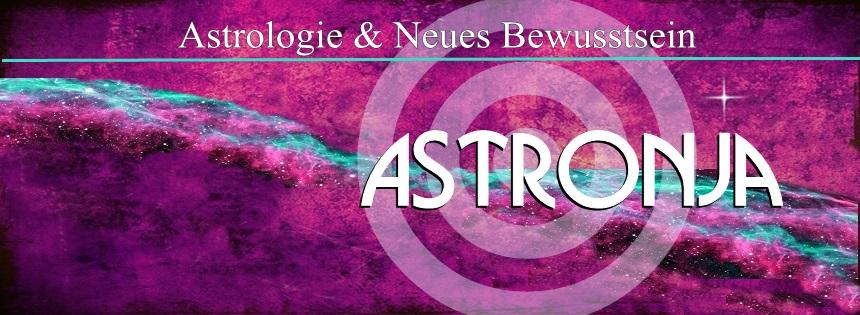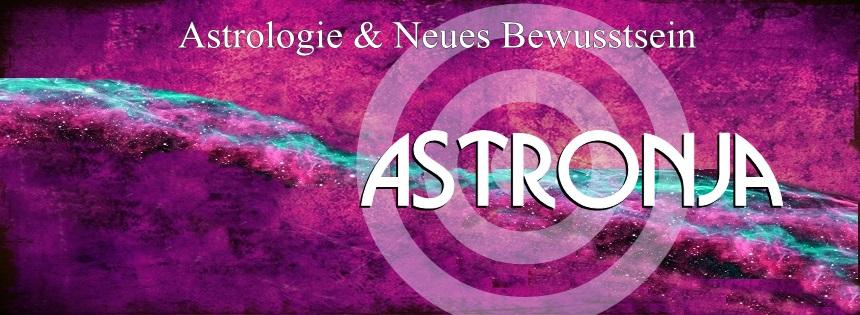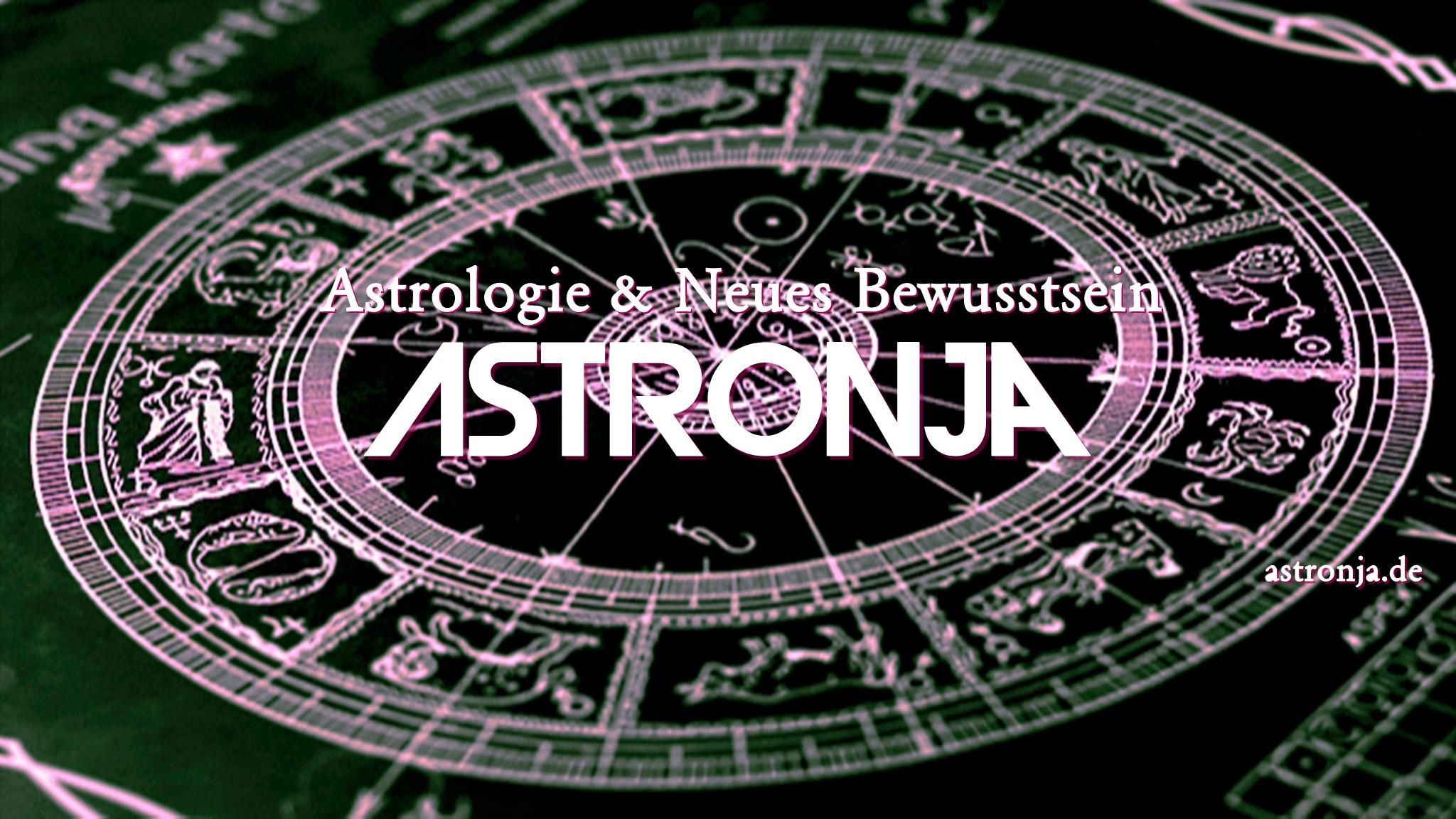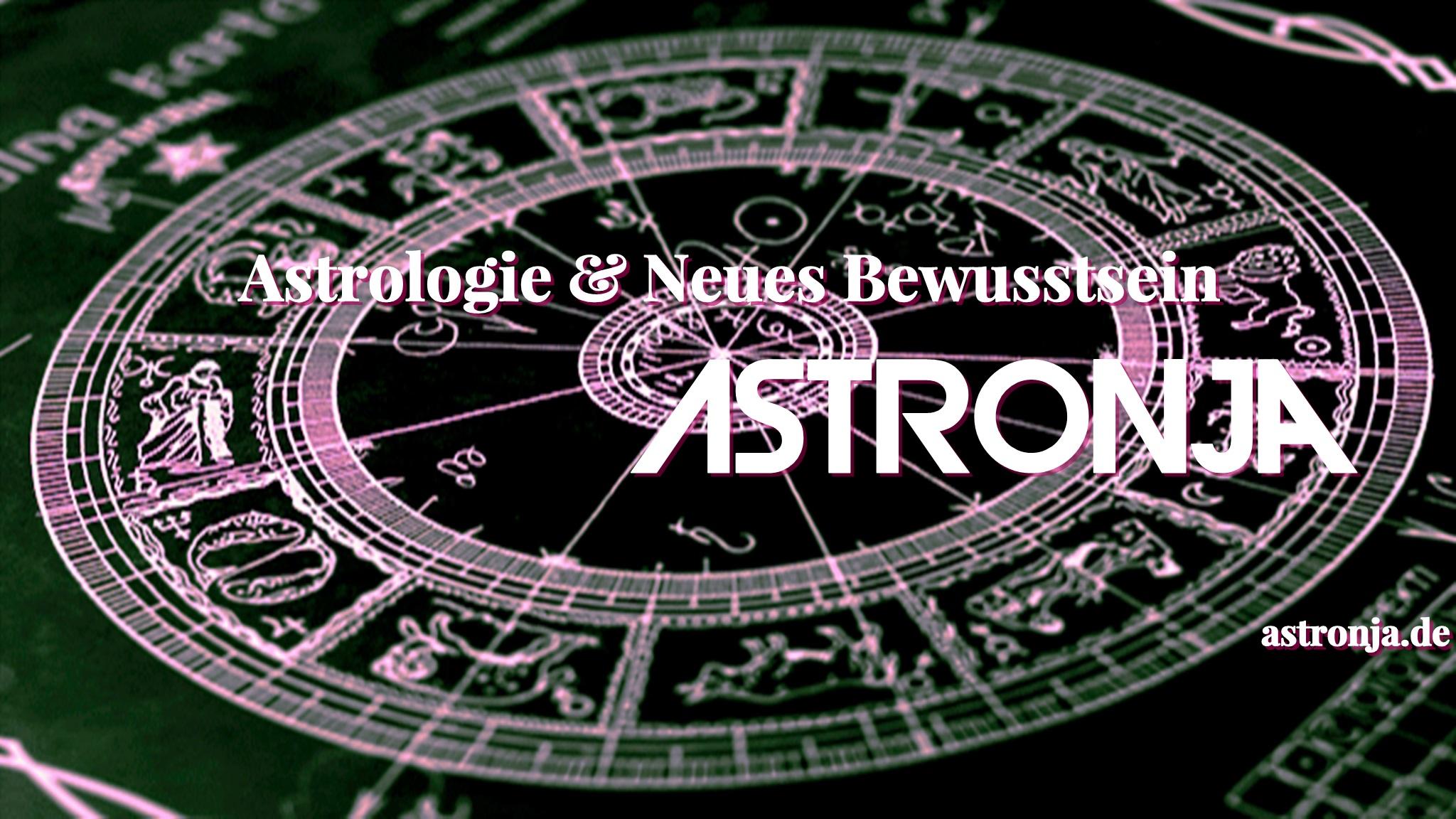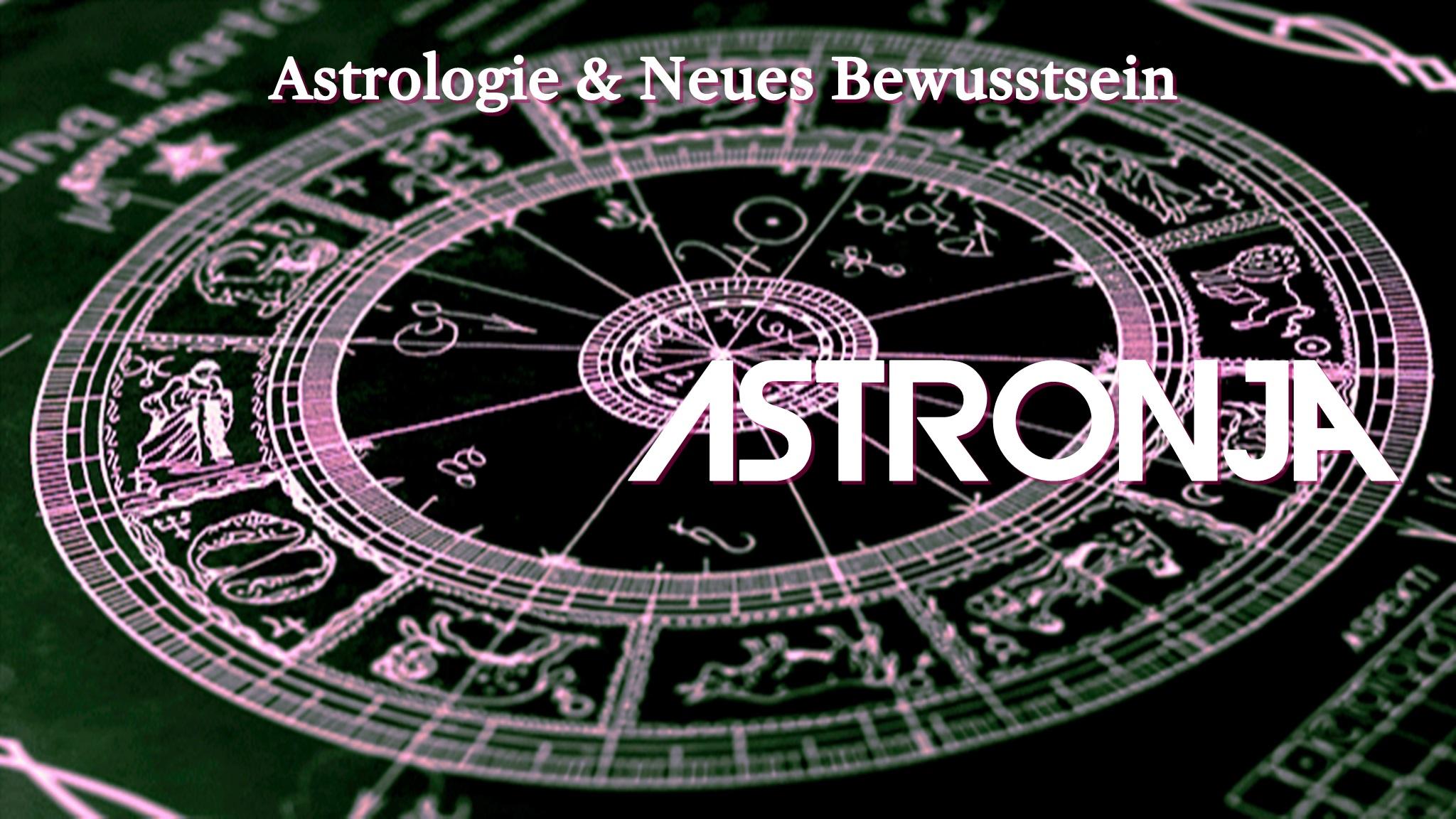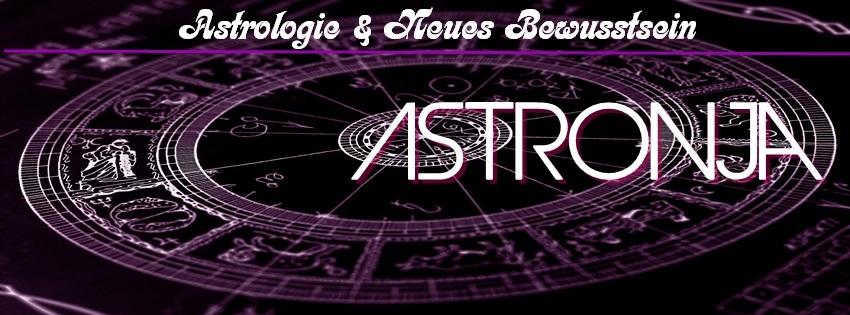
Avant Garde als Logo, welche Schrift ist kompatibel?
für ein Logo (8 Buchstaben) habe ich mir die geometrische Schrift Avant Garde ausgesucht. Für einen Untertitel b. z. w. kurze Beschreibung benötige ich nun einen Schrift, die mit Avant Garde kompatibel ist. Ich habe mich mittlerweile (gefühlt) durch das halbe Internet gelesen aber so wirklich fündig bin ich dabei nicht geworden. Weil mir das Forum von Typografie auch einige Male angezeigt wurde, habe ich mich entschlossen hier anzumelden. Ich habe gesehen, dass schon viel über Avant Garde geschrieben wurde aber mir fehlt wohl der entscheidende Hinweis. Ich freue mich jedenfalls über eure Vorschläge und bedanke mich für eure Aufmerksamkeit.
Die Schrift, welche Du zur Avant Garde suchst – wofür ist die genau gedacht? Nur für eine Unterzeile im Logo? Für ganze Fließtexte? Als ersten Suchfilter würde ich eine Serifenschrift empfehlen, damit eine ausreichende formale Spannung zwischen dieser und der Avant Garde entsteht. Eine Serifenlose dürfte sich in den allermeisten Fällen mit der sehr ausgeprägten Logoschrift beißen.
Zur Inspiration wäre »Fonts in Use« ein Tipp, um zu schauen, ob es dort geeignete Schriftkombinationen mit der AG gibt (Arno zum Beispiel).
danke für deinen tollen Link, ich habe mir die Seite angeschaut  und finde sie überaus inspirierend und spannend, vor allem zeigt sie mir einen Einblick in meine fast unbegrenzten Möglichkeiten, was das Kombinieren der AG mit anderen Schriftarten betrifft.
Ich habe letztes Jahr im Mai mit einen Blog angefangen und dort habe ich zwei Bilder (ähnlich Titelbilder) reingesetzt, mit dem Namen  und Untertitel von meinem Blog. Nachdem ich mich in den letzten Monaten, was den Blog betrifft, fast ausschließlich mit Content, Responsiv, CSS, HTML, Java Script und haste nicht gesehen beschäftigt war, ist mir jetzt nach etwas Kür. Eine neue Schrift für den Fließtext steht auch noch an. Ich schreibe dort in Times Roman, weil ich die Schrift immer noch klasse finde, obwohl sie ihm Moment scheinbar alles andere als Hip ist aber gegen Arial und Calibri bin ich allergisch. Ich muss mich da aber auch erst noch reinlessen, wie und wo ich die Schrift ändern kann, aber wenn soweit ist und ich weiß was ich will, dann kriege ich das auch noch hin.
Unter meine Favoriten  für das Logo war auch die BUSORAMA (habe lange gesucht, bis ich ihren Namen fand) , die ist hier kombiniert mit Binner und Souvenier. Mir erscheint  die Avant Garde aber  ein Ticken futuristischer b. z. w.  zeitloser. Dein Link ist jedenfalls große klasse, auch bringt er back a lot of memories.  :-)
Wenn ich mich mal einmischen darf: so wird das nichts.
Wir wissen gar nicht, welchen Charakter der Text hat und in welche Richtung die Reise gehen soll. Könntest du uns das Logo und ein paar Textproben für die Unterzeile  mal zeigen, vielleicht auch mit der momentanen Lösung und was dir daran nicht gefällt?
Es gibt manchmal sehr gute Gründe, einen Entwurf nicht in der Öffentlichkeit zu zeigen – zum Beispiel, weil mit dem Kunden Verschwiegenheit vereinbart wurde. Außerdem denke ich schon, dass man gewisse Empfehlungen zum Kombinierbarkeit einer gegebene Schriftart treffen kann, auch wenn man die konkrete Gestaltung nicht zu Gesicht bekommt. »So wird das nichts« ist mir persönlich als Aussage in diesem Fall zu kategorisch, zu kompromisslos und auch zu harsch einem freundlichen Neumitglied gegenüber.
danke für euer Interesse, das freut mich sehr. Die „alten" Titelbilder sind in meinem Blog (astronja.de) und dürfen gerne angeschaut werden. Ich hatte das Titelbild für meine FB- Seite gemacht, der Blog kam erst später. Damit es einheitlich aussieht, hatte ich das Titelbild dann auch im Blog verwendet, daran ist nichts schlecht aber ich denke, das geht noch viel besser. Ich habe schon verschiedene Variationen ausprobiert von denen mir auch einige gefallen aber während dessen kam mir der Gedanke, dass es vielleicht besser ist, wenn sich die  Schrift von den Titelbildern,  in Text oder Überschrift wiederholt. Daraufhin habe ich weitere Möglichkeiten entworfen und wieder verworfen, weil sie für den Untertitel entweder zu eng und klein (z.B. Arno) sind oder zu  stino aussehen. Was die Überschriften in meinem Block betrifft, bin ich gerade damit beschäftigt herauszufinden, wie die Schriftgröße und die Fonts  im CSS -Style -Sheet  geändert werden können. Ich habe dafür nun das Simple Custom CSS Plugin installiert aber mich noch nicht über die Vorgehensweise der Inbetriebnahme informiert. So kommt eins zum anderen und ich von Hölzchen auf Stöckchen, nur weiter bin ich noch nicht.:-?
Meine Entwürfe kann ich gerne hier hochladen, würde mir aber lieber vorher eure freie Meinung oder Ideen (unbeeinflusst von mir) dazu anhören. :-)
Danke, und einen schönen Tag allerseits. :-D
Hallo und Willkommen, Persephone,  :huhu:
schön, dass du dir solche Gedanken um deine Website machst. :rockon:  Das ist heute ja eher selten. :-(
Da du uns dazu ermuntert hast, deine Website zu besuchen, hab ich das mal gemacht. Der sehr magere graue (?) Text auf lila Hintergrund, der beim Überfahren rosa wird, könnte für Besucher, die keine Adleraugen haben, schwierig zu lesen sein. Ansonsten sieht (fast) alles auf den ersten Blick prima aus. Ich muss allerdings zugeben, dass mich das wunderschöne Hintergrundbild deiner Website schon sehr irritiert hat, da es einfach nicht zum Inhalt passt. Es gibt doch sicher auch schöne astrologische (oder eben neutrale) Hintergrundbilder, die die Aussage deiner Website nicht unterlaufen. Zwei zu einander im Widerspruch stehende Disziplinen, Astrologie und Astronomie, hier einfach zusammenzuwerfen, erzeugt mglw. Dissonanzen und ist m.E. nicht ideal geeignet, um deine Inhalte klar zu kommunizieren.
Danke, das werde ich bei der Neugestaltung berücksichtigen.
So, jetzt kommen hier auch mal  einige Vorschläge von mir. :cheer: Es sieht immer gleich ganz anders aus, wenn es gepostet ist.
Ich weiß nicht, ob es wichtig ist, ob der Hintergrund hell oder dunkel oder mit Bild ist, aber ich denke, dass es wichtig ist, dass die Stimmung stimmt. Ich würde eher zu einer einfachen und klaren, klassischen Schrift tendieren, wenn es über einem Bild sein soll. Vielleicht kann man das Bild auch als Füllung für die Schrift nehmen – dann hätte man beides – hellen Hintergrund und Bild …
Hallo Schnitzel, was ist denn für dich eine klare klassische Schrift und mit welcher anderen würdest du sie kombinieren?